这位大叔靠为日本地铁创作的导视标识字体而走红网络。他不仅再次证明设计高手在民间,还证明了设计高手可能根本没学过设计。
日本不乏平面设计大师,前有“国宝级”海报及字体设计大师田中一光,现有无印良品设计总监原研哉。尽管作品水平高超,但因为他们科班出身的背景,也并未让人感到意外。反倒是近年一位本职担任保安的67岁老爷子,因富有标志性的字体创意制霸设计东京地铁标识字体创作领域。
这位地铁保安名叫佐藤修悦,他的设计职业履历基本上简单到可以用两句话概括。年轻时曾在银行、咖啡店工作,其中唯一和设计相关的工作大概就是在报社负责过排版。步入中老年后佐藤修悦开始了自己的保安生涯,2004年其所工作的在JR东京新宿站东口实施改造工程,为了方便地铁乘客寻路,他使用胶带制作指路牌。
从此,佐藤修悦的创意便一发不可收拾,作品也可丰富了。
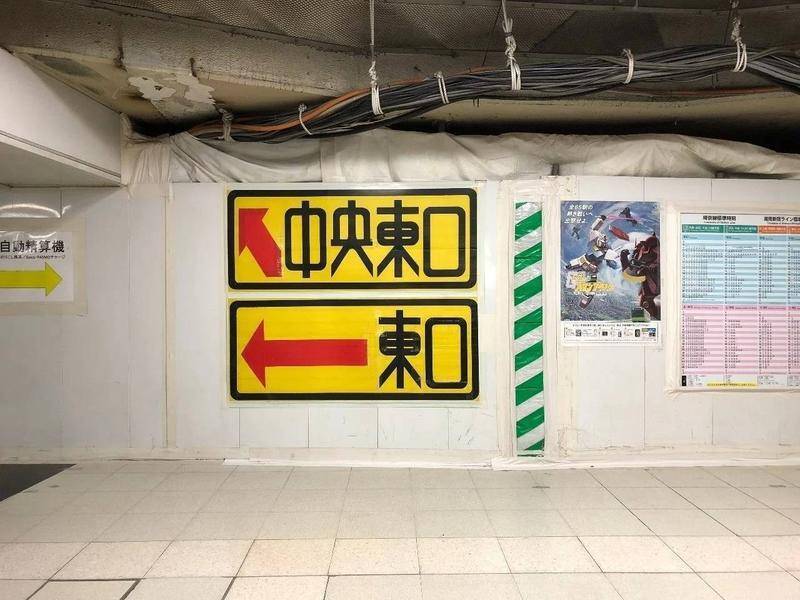
佐藤修悦的胶带地铁标识作品,具有简单易懂的指示功能
最初,修悦仅仅使用工地现有的白、黑、黄三色胶带进行自发性的设计。其制作的标识牌受到好评后,车站授权修悦进行“官方创作”,还批准修悦追加使用红、蓝、绿三个颜色的胶带。
经过个人博客和媒体的曝光之后,2007年的修悦已经成了有一定名气的真·地铁告示牌设计大师。不仅在JR东京日暮里站的建筑项目中担任了两个大型项目的制作工作,还被授予站长特别奖,同时获赠奖状和奖品——两双袜子。
佐藤修悦认为边缘圆润柔和的字体会让地铁中忙碌的人们感觉更好
佐藤修悦每次进行胶带创作,都会先在告示板上用胶带或暗线标出字体的外框,再用直线的胶带在标记好的区域内进行贴制,然后根据形状切割边缘和转角中多余的部分,以让字形变得圆润。对此,佐藤修悦的解释是:“在忙碌的车站里,柔和的圆角会让人们体验更好。”
修悦体的特点是造型简单,可以在短时间内读取。同时,横线间曲线和转角的部分会根据字数、文字大小而因地制宜地发挥。这样一来,即使是同一个字,每一次出现也可能具有不同的字形。
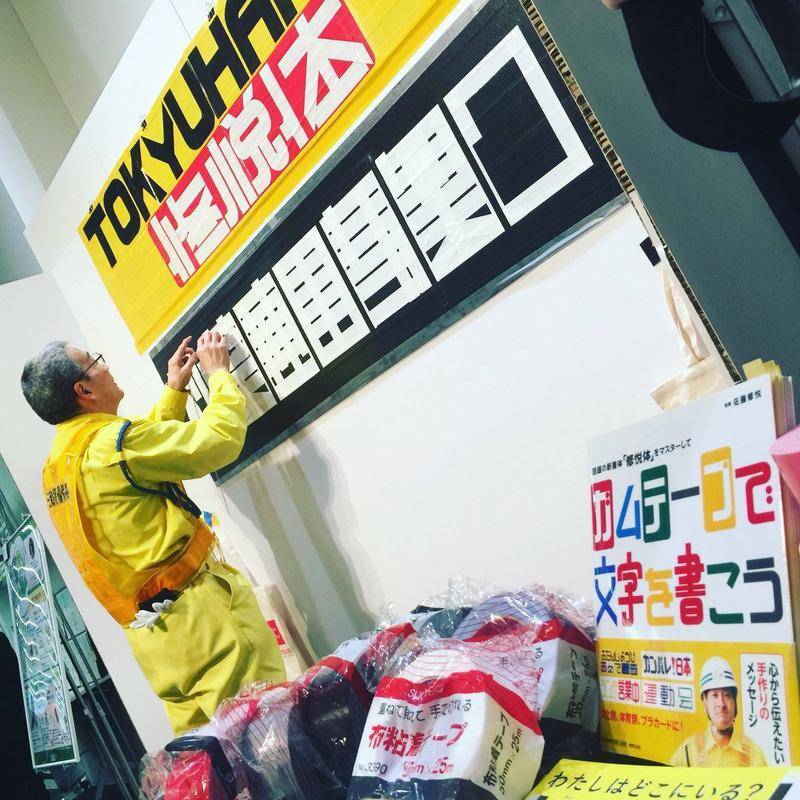
修悦的胶带字体创意是先贴出大致的字形轮廓,再用美工刀切割掉多余的部分
出名之后,佐藤修悦接连举行字体设计相关的展览,还监制书籍出版并举办了签售会。
他的故事不仅再一次说明设计高手在民间,还说明设计高手其实可能根本没学过设计。
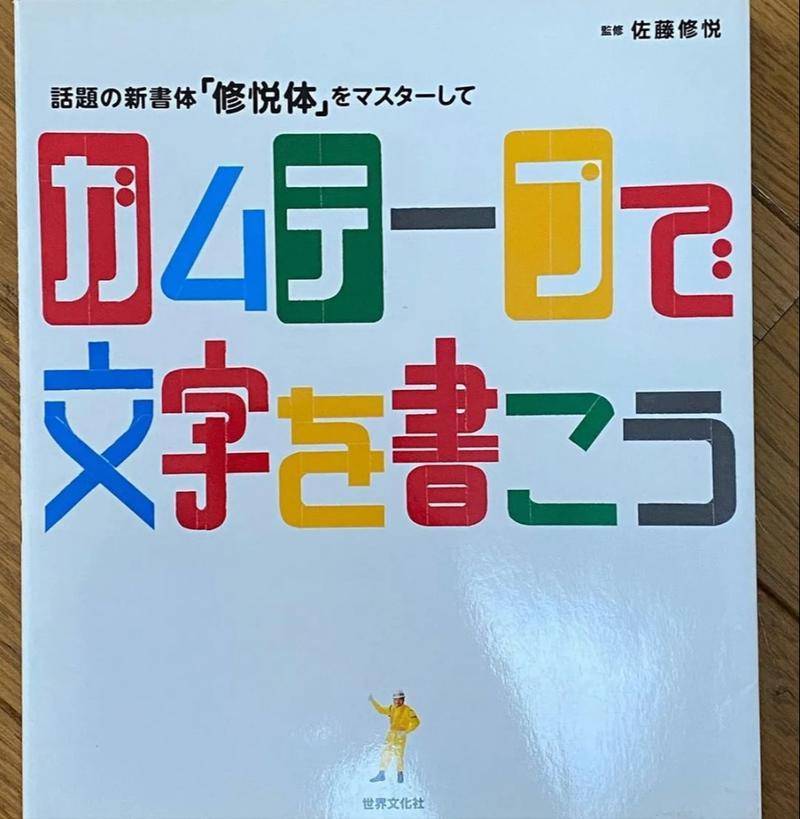
佐藤修悦监制的出版物《用胶带书写文字》,其中介绍了如何使用“修悦体”进行创作
尽管修悦没有接受过正规平面设计培训,但日本公共交通中的标准化标识系统其实已经深入人心,很难说他是否早就在生活的耳濡目染中浸润了这套字体设计之道。
早在1963年,日本就开始在高速公路中使用标识文字系统“日本道路公共团体Original字体”,其也被简称为“公团文字”。这种字体力求使驾驶员能够在车辆距离标识牌120米的地方就可以读出字意内容,因此会以简单的横线为主要组成部分,对于笔画复杂的汉字往往仅保留字形轮廓,经典的例子就是高速道路标识上简化后的“鹰”字。
曾广泛用于日本高速公路系统的“公团文字(上)”简化了一般日本汉字(下)的外形,可以让人快速辨别字形
虽然2010年之后,“公团文字”因“非标准日本汉字”而逐渐被弃用,但“公共标识文字要像图形一样简单易读”这一理念已经深入人心,佐藤修悦的字体设计也正是体现了这一道理。
同时,修悦体的标识牌中似乎也沿用了日本道路标识系统中的官方配色。比如以柔和的蓝白色搭配表达一般指引;黄色代表警戒;红色则多与规章、禁止有关。使用者们正是因为对这样的标识颜色系统已经形成一定的条件反射,所以在阅读佐藤修悦设计的标识牌时也能快速进行判断。
日本公共道路标识的色彩搭配系统似乎也为佐藤修悦的字体设计带来了影响
如果说佐藤修悦的字体设计是受日本公共道路标识系统潜移默化影响后的总结性输出,那么他在非功能性场合进行的胶带贴制就更贴近艺术化的创作行为。
比如在商场开业的庆祝字牌中,佐藤尝试了高矮不一的字体搭配,还在空隙中加入了圆形的装饰,增加了创意成分,这让他的作品更像是非标准化的即兴手作胶带涂鸦。
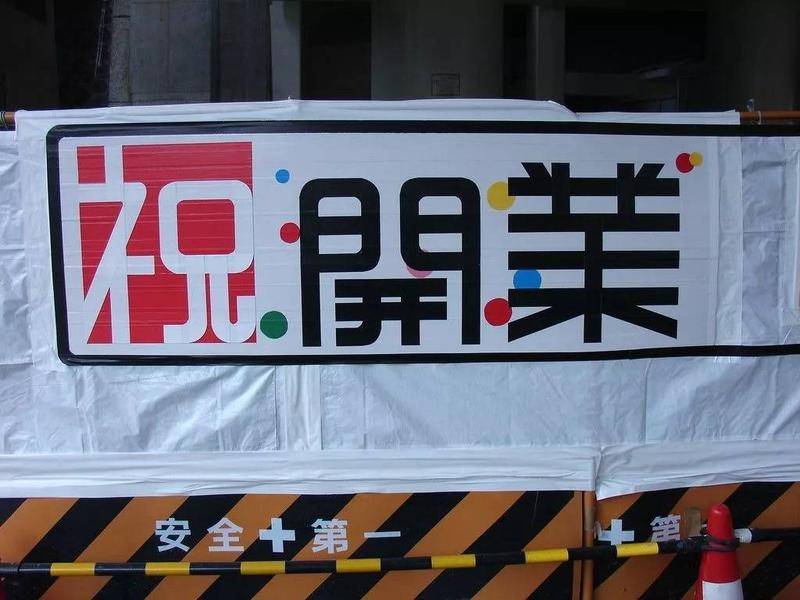
开业现场出现的修悦体胶带文字,弱化了功能性,侧重了设计美感,体现了佐藤修悦的创意性
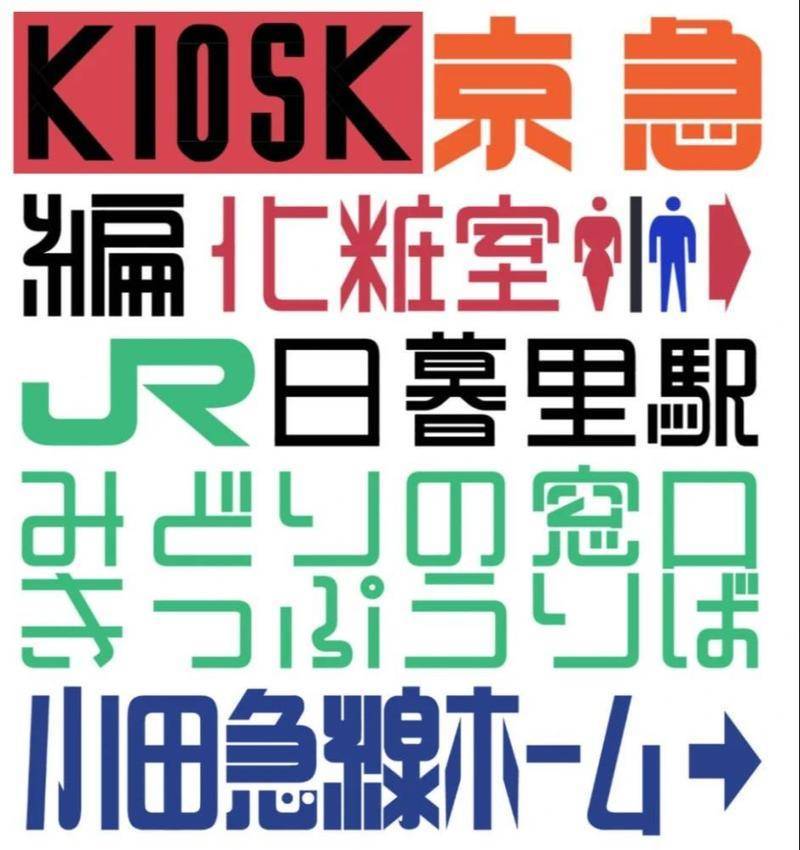
佐藤修悦的地铁标识设计,从英文到假名,根据需要的大小可以进行灵活的即兴创意
如今,出名后的佐藤修悦并没有以网红自居。他仍然主业从事保安工作,同时在标识牌中继续字体设计实践,偶尔去做讲座和展览。
他的故事说明认真对待自己的工作总是没错的,说不定什么时候就能收获意外的回报。
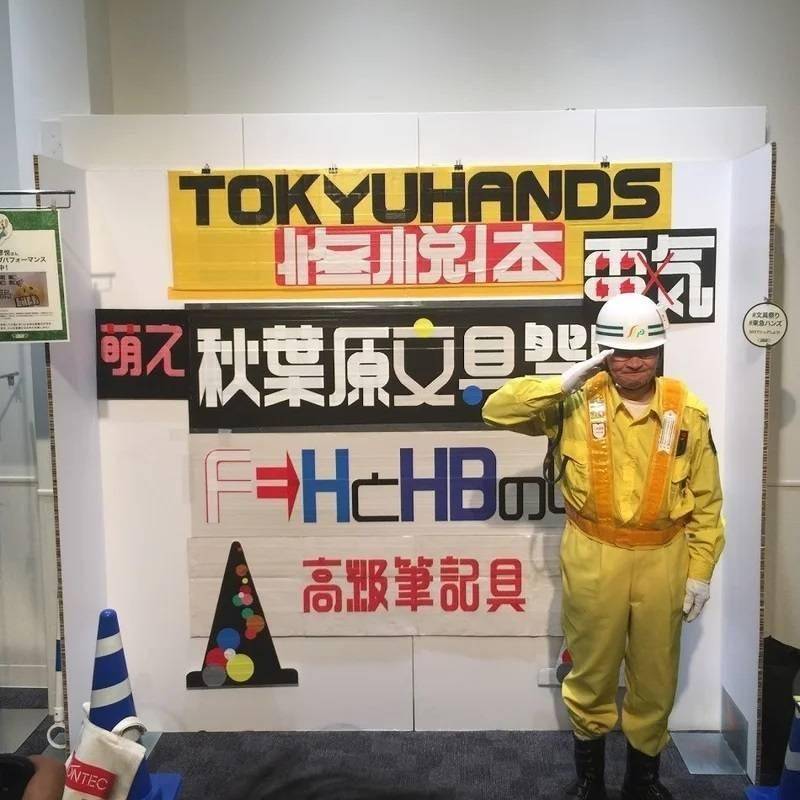
成名后的佐藤修悦,仍然从事着保安的工作,即使在出席活动时,也穿着工作制服